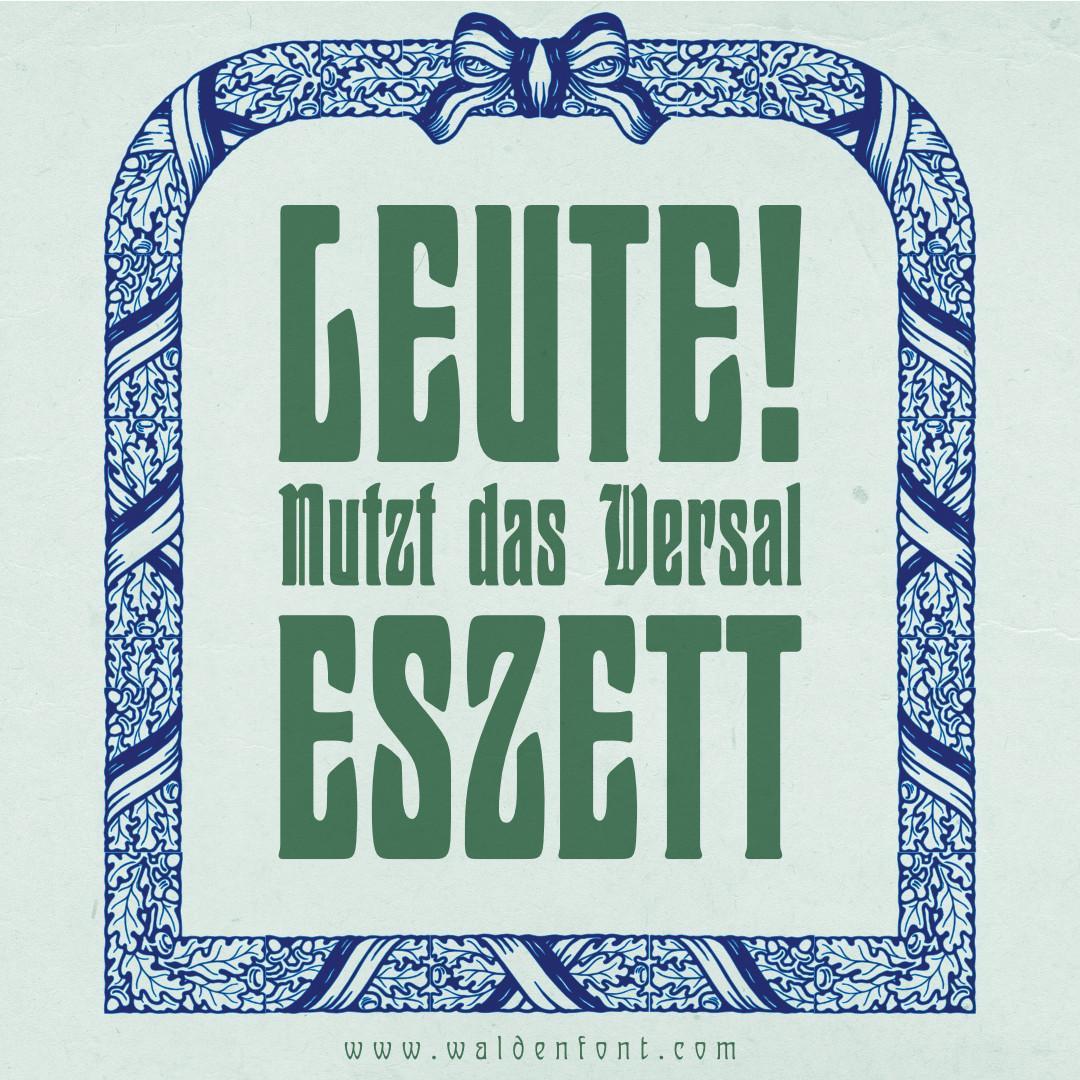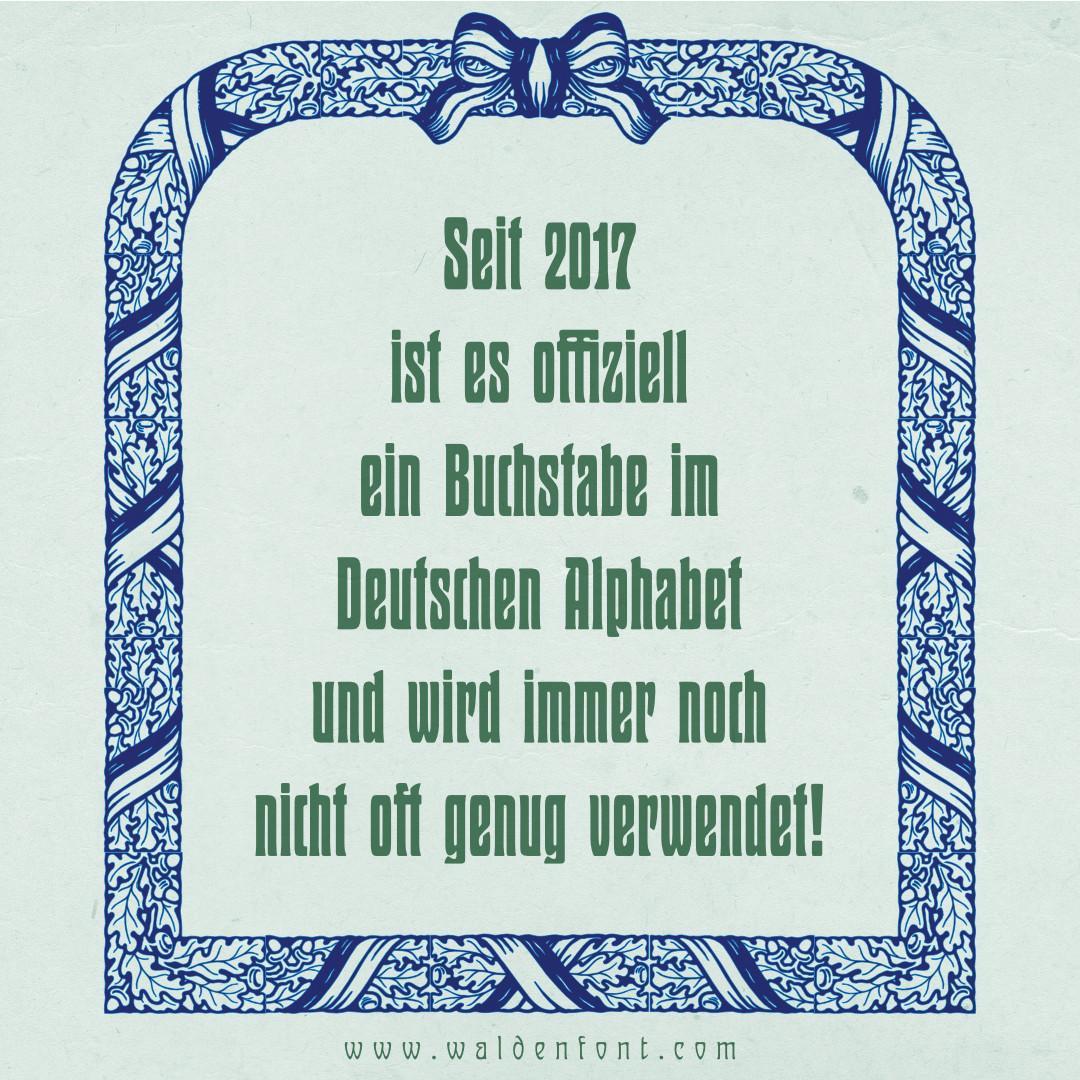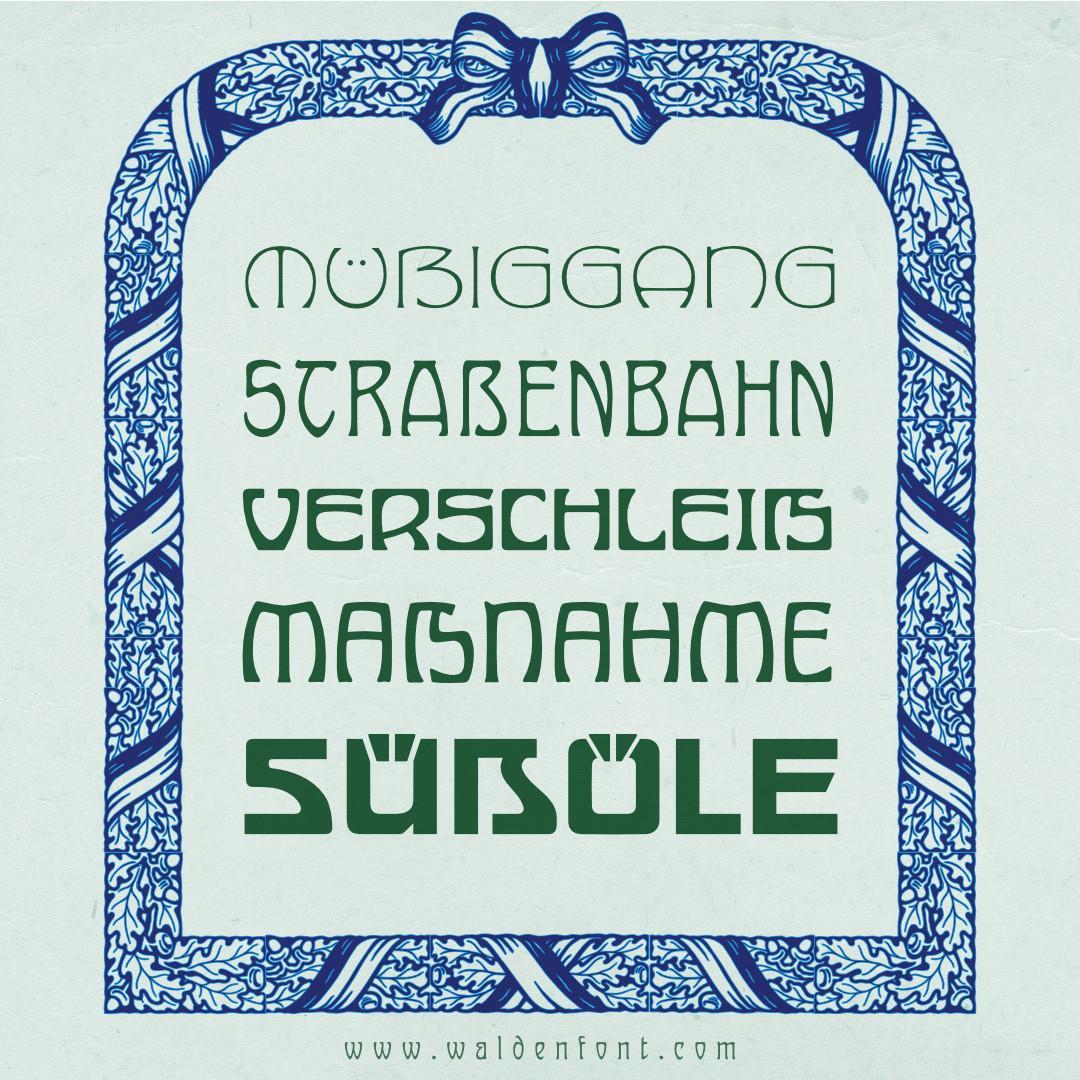
Schrift mit Lang-ſ und Versal-ẞ gesucht und gefunden
Ich war die letzten Tage auf der Suche nach einer Schriftfamilie (Serif und Sans), die über Lang-ſ und Versal-ẞ sowie noch andere Spezialitäten verfügen sollte. Die Suche war erfolgreich. Es sind die Skolar und die Skolar Sans von Rosetta geworden.
Auf dem Weg zu diesem Ergebnis kam diese Übersicht zustande, die ich euch nicht vorenthalten möchte:
Man beachte die Clavo, bei deren kursiven Schnitten die kleine Nase am Lang-ſ nach rechts zeigt – ungewöhnlich bis unbrauchbar.
Interessant fand ich auch, dass in der Pro-Version der Verdana die Grundform des Versal-ẞ gänzlich geändert wurde. Die Form sagt mir zwar nicht so zu, aber sie ist m. E. auf jeden Fall viel besser als eine nur verbreiterte Sulzbacher oder Knuspenform für die Majuskel.
Und bitte schaut euch auch die ſz-ligaturige Form der Inknut Antiqua an. Da muss man schon sehr mutig sein, damit etwas zu setzen.
In der Tat, dafür würde ich mir aber, zusätzlich zu Bẞ, auch eine f ſ -Gegenüberstellung wünschen ... Gerade auch, damit die falsche Nase mehr auffällt ...
Ja, Inknut ist arg gewagt ...
Bei meinen Schriften ist es ja einfach, genau diese Eigenschaften zu finden, immer wenn diese 2 Icons zu meinen Schriften auftauchen, ist auch ſ und ẞ vorhanden:
Und bei manchen gebrochenen Schriften sind die ẞ oft nur Platzhalter, und kaum wirklich passend zur Schrift ausgearbeitet, weil man mit diesen Schriften ohnehin keinen sinnvollen Versalsatz hin bekommt.
auch eine f ſ -Gegenüberstellung wünschen
Stimmt Mueck, ein f hätte ich noch neben das ſ stellen sollen. Na, vielleicht beim nächsten Mal.
Und das A steht dermaßen unter Spannung – da möchte man als Buchstabe wirklich nicht direkt daneben stehen, wenn der Querstrich reißt! :-o